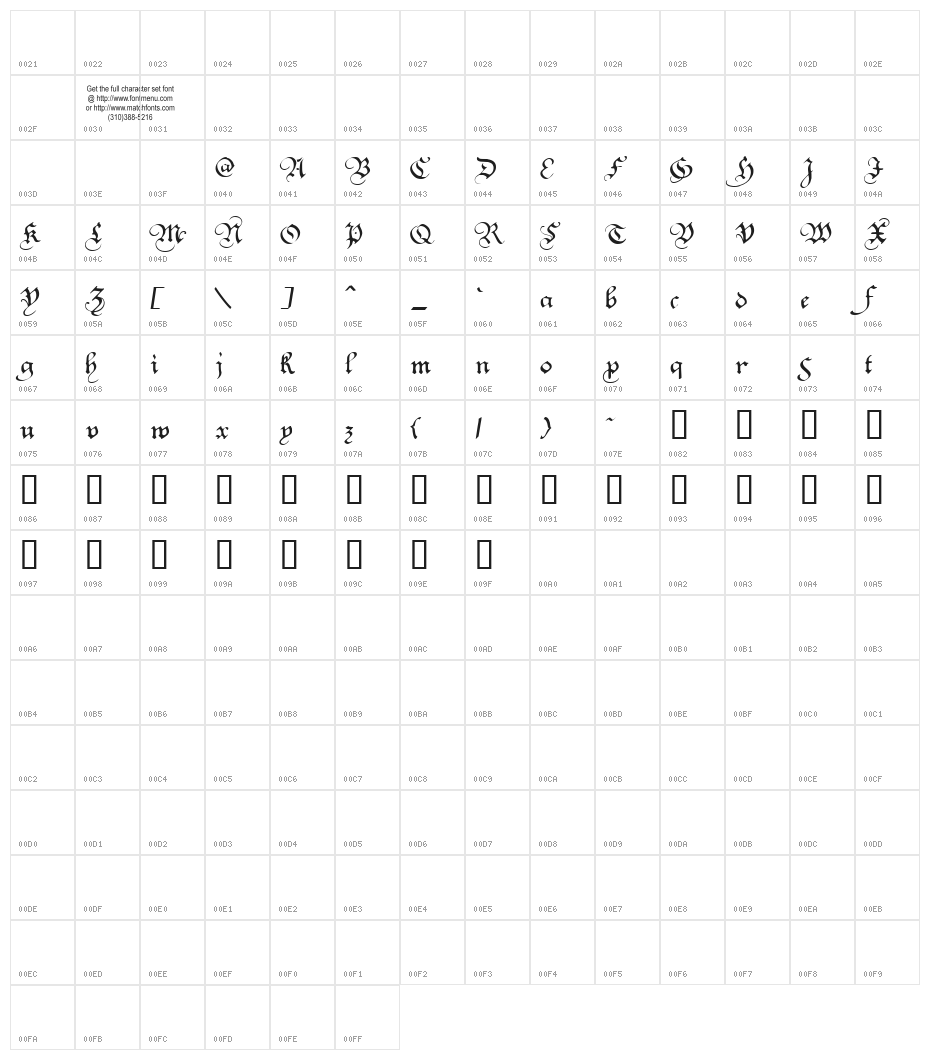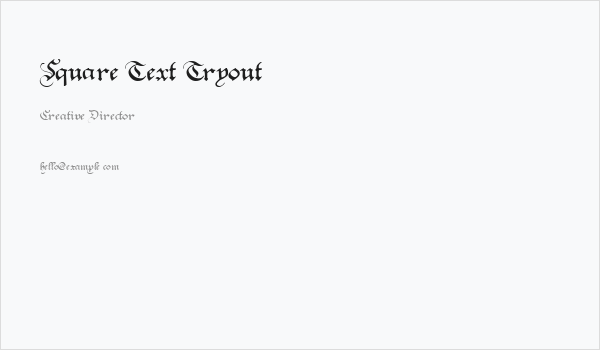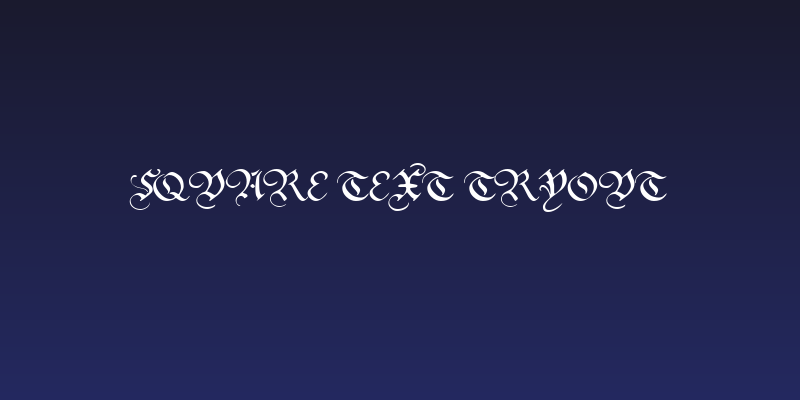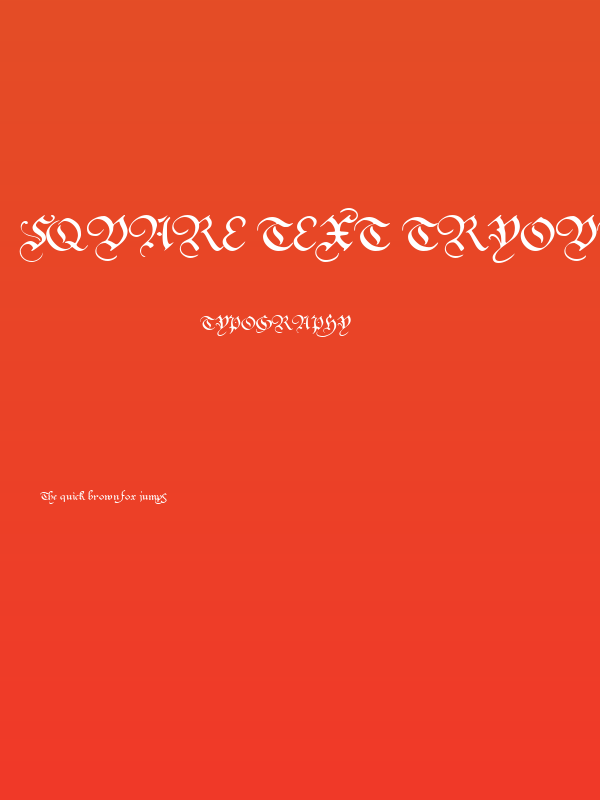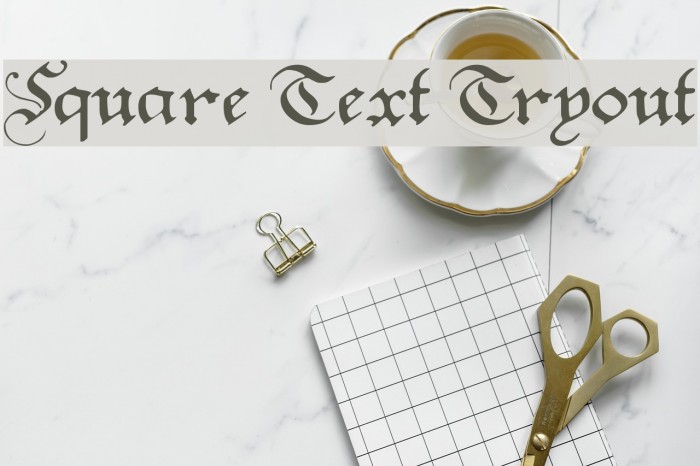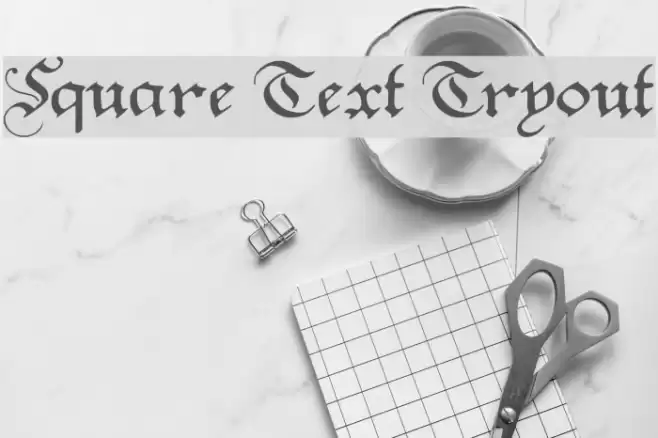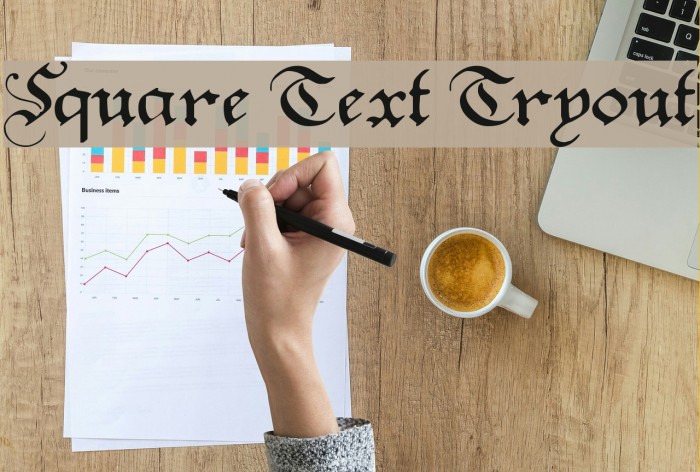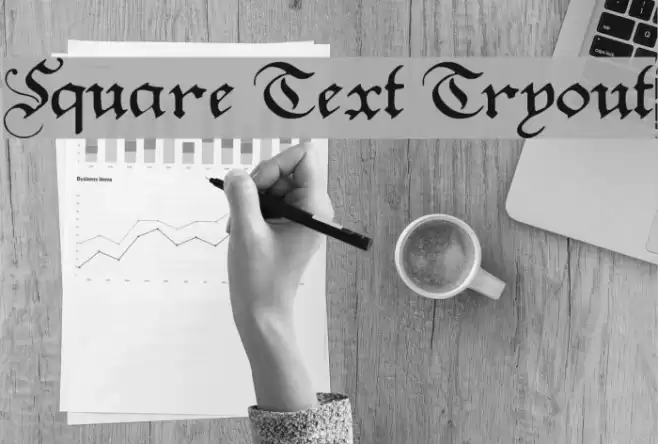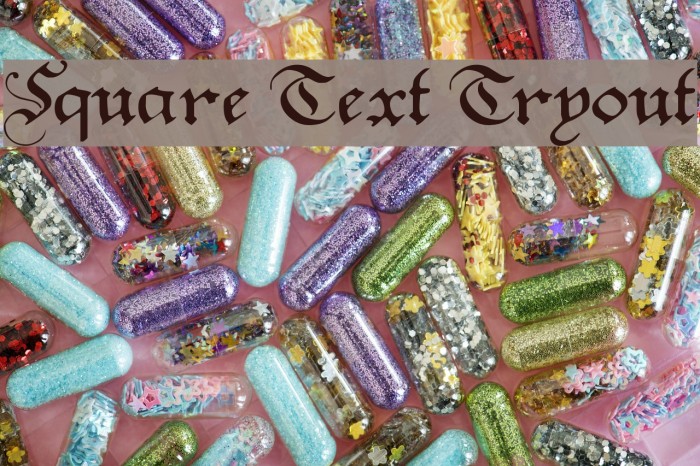
Square Text Tryout Font
| Cas d'utilisation | Headlines, Logos, Decorative text |
| Projets proposés | Ideal for historical documents, wedding invitations, book covers, and branding that requires a vintage or traditional touch. |